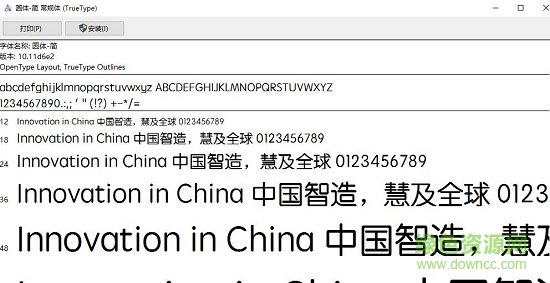
圓體簡免費(fèi)字體
圓體-簡 常規(guī)體是一款粗細(xì)適中的圓體字體,該字體的拐角處均是圓形,給人的感覺比較溫柔,沒那么犀利,需要更多ttf字體的小伙伴們快來綠色資源網(wǎng)下載吧!
圓體的變體有哪些?
變體有為幼圓體、琥珀體等,字體清晰、端正、嚴(yán)肅,適合于報(bào)紙大字頭、圖書封面、招牌、廣告、網(wǎng)站標(biāo)題的制作。